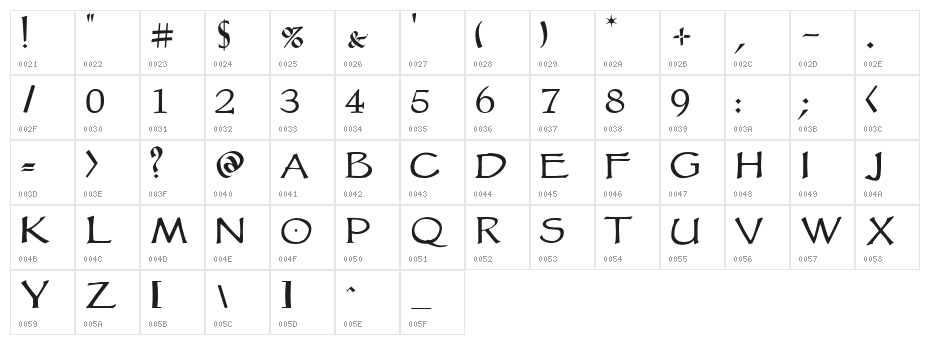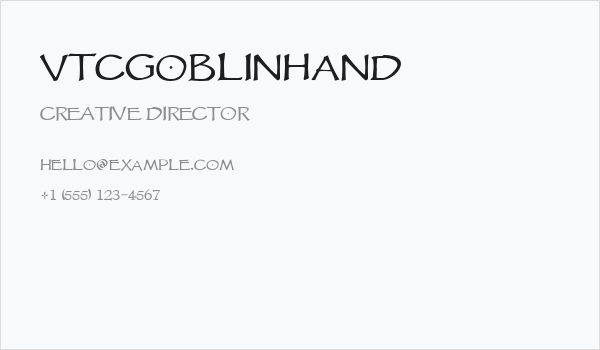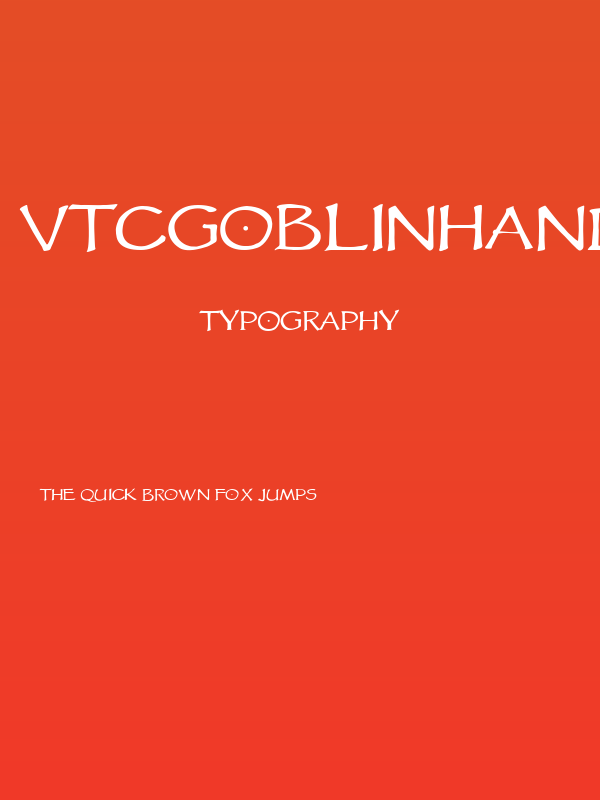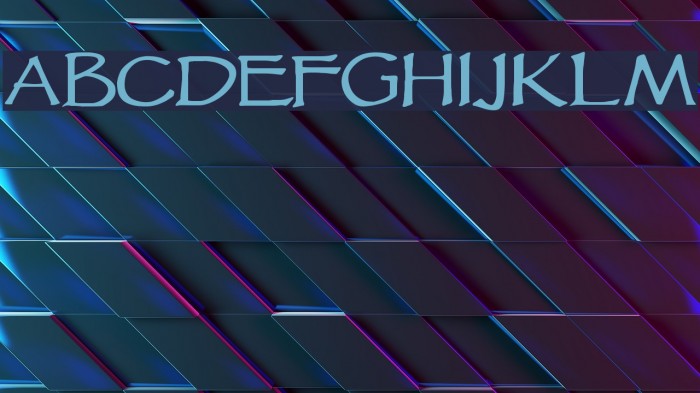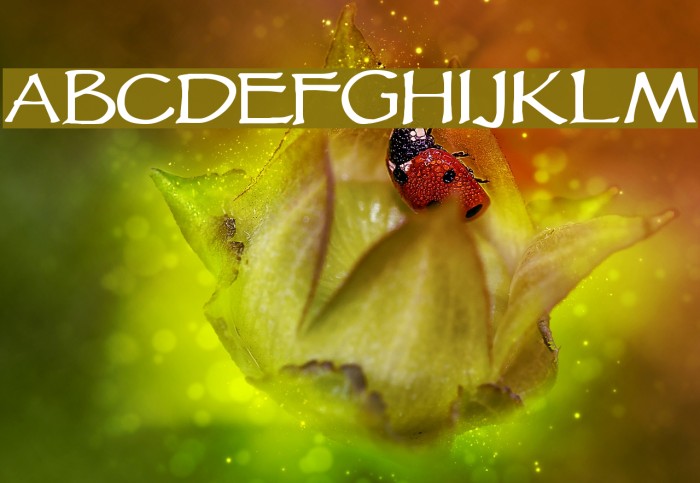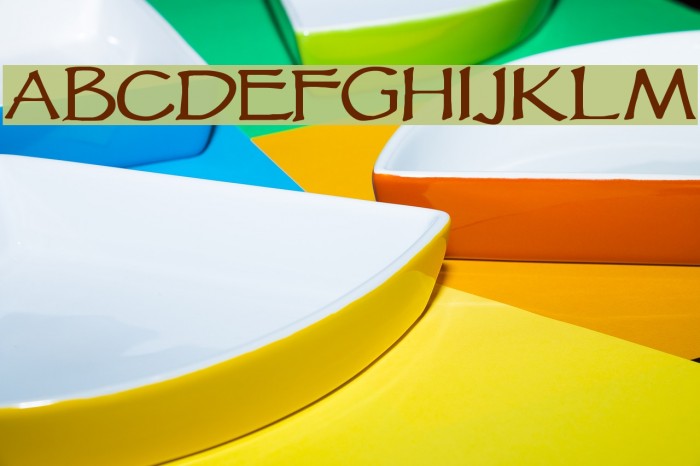
VTCGoblinHand Font
| حالة الاستخدام | Logos, Headlines, Posters |
| مشاريع مقترحة | Ideal for fantasy-themed designs, children's books, playful branding, and creative posters. |